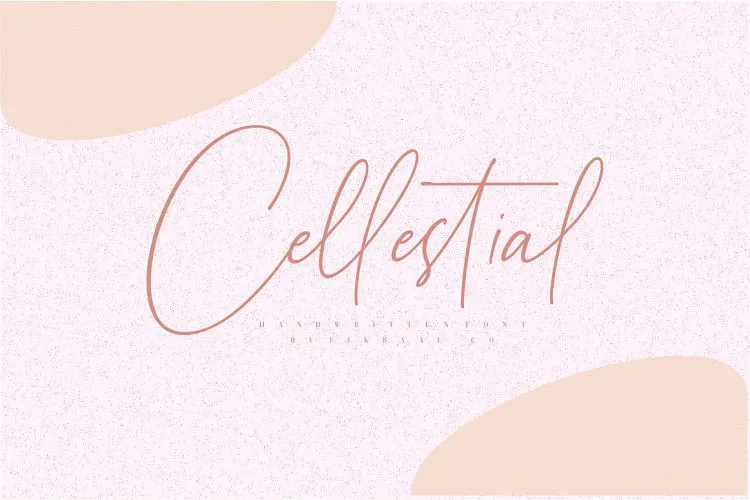
Cellestial Handwritten Font – Download Grátis
A Cellestial Handwritten Font é uma nova opção para aqueles que buscam um equilíbrio entre elegância e modernidade na criação de designs. Ideal tanto para trabalhos profissionais quanto pessoais, essa fonte é perfeitamente adaptada a títulos, invitations, embalagens de produtos, design web, postagem no Instagram ou redes sociais, entre outros formatos de mídia social. O seu charme elegante e estilo moderno tornam-a uma escolha inteligente para qualquer projeto que exija um toque único e atraente. Seja em cartões de visita, logotipos ou até mesmo em fotografias, essa fonte é perfeita para quem deseja dar um novo olhar aos seus designs. Sem dúvidas, ela é uma escolha ótima para designers gráficos que buscam equilibrar elegância com praticidade e criatividade.